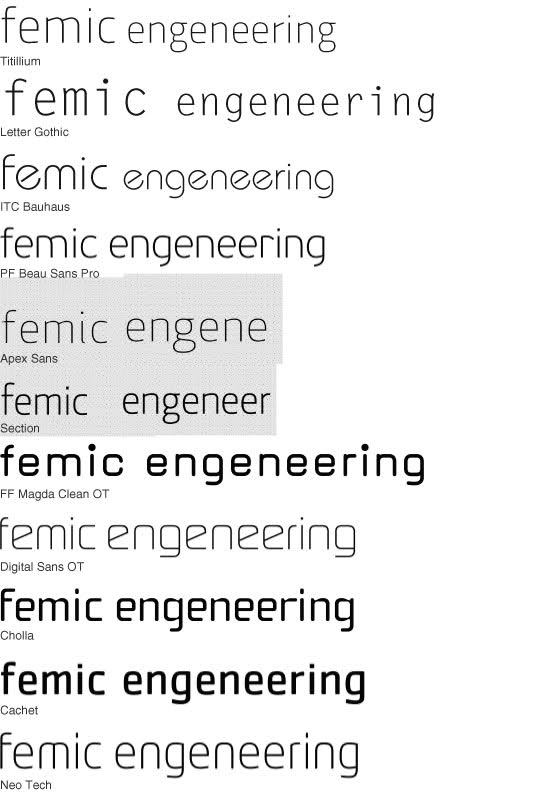
Suche Schrift für den Bereich Elektronik
Mit Hilfe eurer Links und Tipps hab ich mich mal durchgeforstet und eine Auswahl erstellt.
Gibt es bei den Schriften irgendein absolutes No-Go? Z.B. die Digital Sans - ist das ein Screenfont?
Ich würde engineering zunächst richtig schreiben. :D
Spontan:
Digital Sans ist mein Favorit.
Letter Gothic und Bauhaus gehen gar nicht.
Jo, ich würd auch sagen Letter Gothic geht gar nicht, Bauhaus gefällt mir bei näherer Betrachtung auch nicht so gut... Die Titilium find ich recht gut (ach was!), vielleicht noch die Section, alles andere ist mir entweder zu fett oder zu... speziell :D
Ich würde engineering zunächst richtig schreiben. :D
Bei so viel "i"s und "e"s darf man sie ja auch mal vertauschen :lol:
Die Titillium, BeauSansPro, Section und Digital sind auch in meiner näheren Auswahl.
Die Digital ist also kein Screenfont?
Warum sollte die ein Screenfont sein?